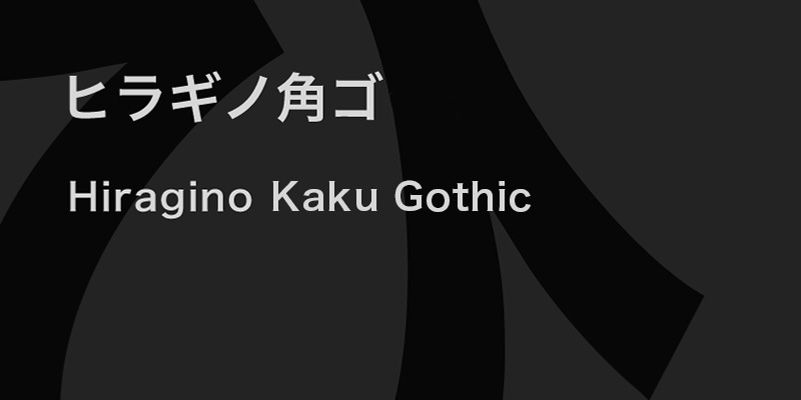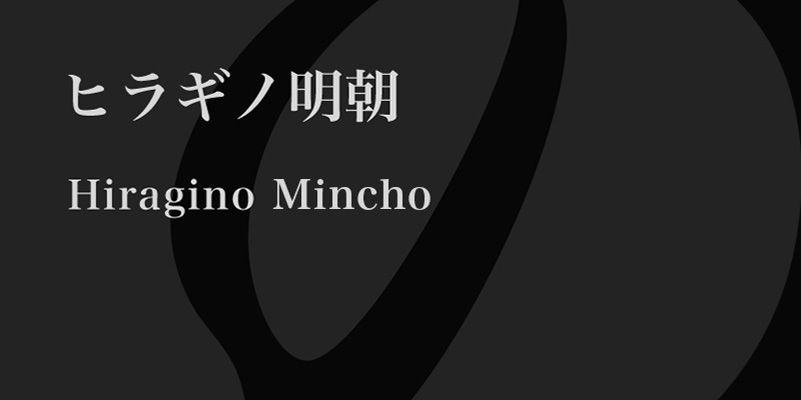
提供する書体は「ヒラギノ角ゴ ProN W3/W6」と「ヒラギノ明朝 ProN W3/W6」。広告・動画・Webサイト・書籍など、あらゆるメディアに読みやすく美しい文字をもたらすヒラギノフォントの中でも、最も人気のある書体。
ヒラギノ角ゴ ProN W3
ヒラギノ角ゴ ProN W6
ヒラギノ明朝 ProN W3
ヒラギノ明朝 ProN W6